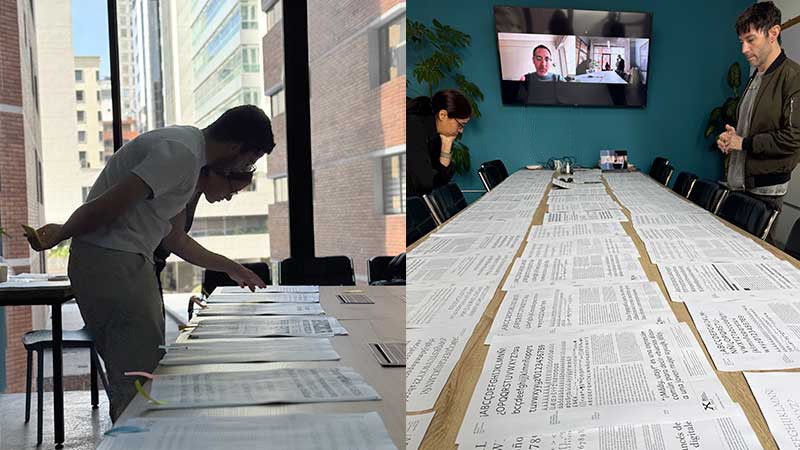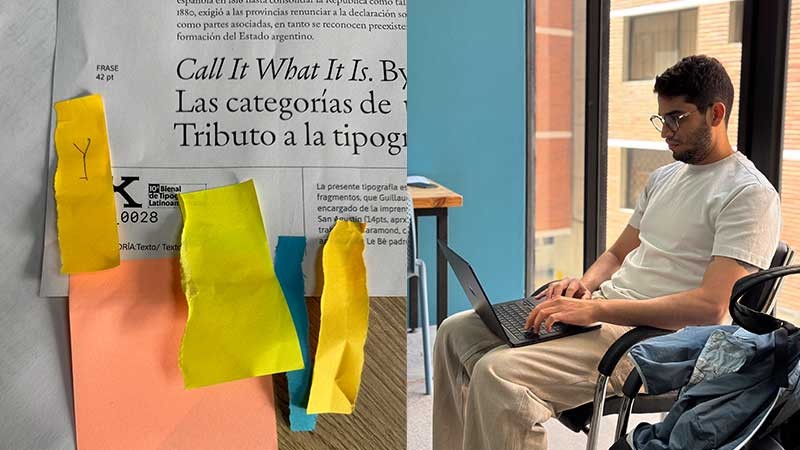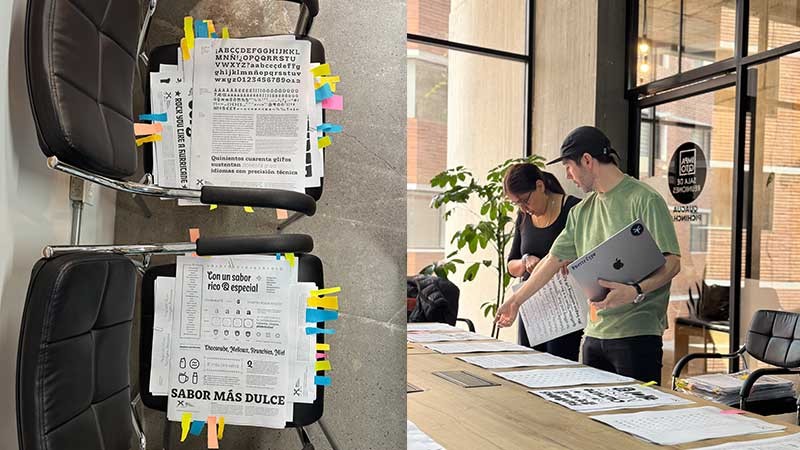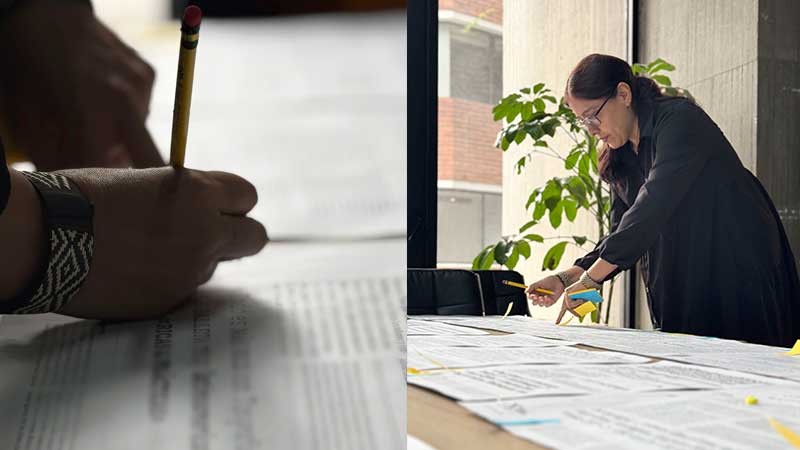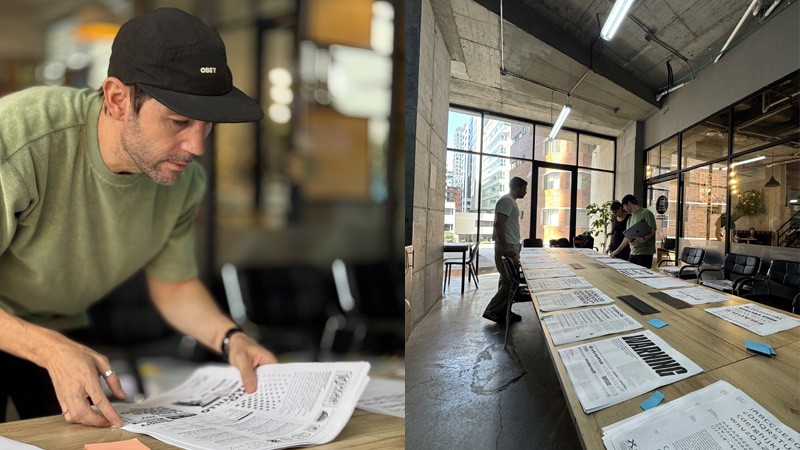
2026 Jura
Jura Tipos Latinos 2026
Por Esteban Salgado M., Coordinador General de la Jura
La Bienal de Tipografía Latinoamericana Tipos Latinos llega a su décima edición en un momento particular de su historia. Veinte años después de su inicio, no solo se consolida como un espacio de referencia para la tipografía en la región, sino que también se enfrenta a la necesidad de revisarse, actualizarse y proyectarse hacia el futuro. Esta edición marca, además, un hito importante, por primera vez la jura presencial se realizó en Quito, Ecuador, recuperando el valor del encuentro físico entre jurados como instancia clave de discusión, contraste y camaradería.
El proceso que dio forma a Tipos Latinos 10 comenzó en junio de 2025, con un enfoque claro en reorganizar el funcionamiento interno de la bienal. A partir de la creación de comisiones de trabajo, el comité pudo distribuir responsabilidades, estructurar y documentar procesos para la construcción de protocolos que permitan sostener y mejorar la bienal en el tiempo. Este modelo no solo hizo más eficiente la gestión, sino que también abrió la participación a distintos miembros, incorporando experiencias y perspectivas diversas desde cada país sede.
Uno de los cambios más relevantes fue la implementación de un sistema híbrido: una etapa de preselección virtual seguida por una jura presencial. Este modelo permitió optimizar el tiempo de los jurados y, al mismo tiempo, generar una instancia final de discusión más precisa. El resultado fue una selección sólida en un contexto de crecimiento significativo: en esta edición se recibieron 768 proyectos, una cifra que prácticamente duplica el promedio histórico de la bienal. De ese conjunto, el jurado seleccionó 75 proyectos y otorgó 3 Constancias de Excelencia.
Este crecimiento también estuvo acompañado por un trabajo sostenido en comunicación. A través de una coordinación entre sedes, se fortaleció la presencia de Tipos Latinos en redes sociales, amplificando el alcance de la convocatoria en distintos países. Paralelamente, se revisaron y actualizaron las bases de participación, reincorporando la categoría Diseño con fuentes latinoamericanas.
Otro frente importante fue el sitio web. En esta edición se realizó una actualización integral que incluyó la recuperación y organización de la información histórica de todas las bienales anteriores, la creación de un repositorio de catálogos y la mejora del sistema de inscripciones y preselección. Este trabajo no solo responde a una necesidad operativa, sino que posiciona a Tipos Latinos como un archivo activo de la tipografía latinoamericana.
La jura estuvo a cargo de Yanina Arabena (Argentina), Iván Castro (El Salvador), Yorlmar Campos (Venezuela), Fermín Guerrero (Uruguay) y Vanessa Zúñiga (Ecuador). Su participación, tanto en la etapa virtual como en la presencial, fue fundamental para sostener un proceso riguroso y abierto al diálogo. Las decisiones tomadas reflejan una escena tipográfica en expansión, con una diversidad de enfoques que va desde desarrollos técnicos complejos hasta propuestas experimentales que amplían los límites del campo.
La selección de esta edición deja ver con claridad el momento que atraviesa la tipografía en América Latina. Hay una mayor madurez en los procesos, una conciencia más clara del contexto y una relación más crítica con las herramientas disponibles que están mutando constantemente.
Este contexto también plantea una pregunta necesaria: qué rol debe asumir Tipos Latinos más allá de la bienal. Mantener una actividad continua permitiría fortalecer su impacto, ya sea a través de programas formativos, desarrollo de contenidos, expansión del archivo o generación de nuevas instancias de encuentro. En un escenario donde la disciplina sigue creciendo, la bienal puede convertirse en una plataforma activa que acompañe ese proceso.
En términos de producción, el comité tomó la decisión de establecer un único catálogo regional en formato digital, distribuido desde Tipos Latinos a todas las sedes. La versión impresa quedará a cargo de cada país, en función de sus posibilidades.
Nada de esto hubiera sido posible sin el trabajo de quienes integraron las distintas comisiones y asumieron responsabilidades específicas en cada etapa del proceso. Esta edición es, en gran medida, el resultado de un esfuerzo colectivo que permitió reactivar la bienal, organizar la jura proyectando las exhibiciones y actividades que se realizarán en distintos países de la región.
Finalmente, agradezco a todas las personas que contribuyeron a hacer posible esta edición. A la Universidad San Francisco de Quito por acoger la jura presencial, a Estudio Pánico por el desarrollo de la identidad visual de TL10, y a cada colega del comité regional que, desde su lugar, aportó a este proceso. La 10ª Bienal de Tipografía Latinoamericana Tipos Latinos no solo celebra lo que ha sido en estos veinte años, sino que abre un camino para lo que puede llegar a ser en las próximas décadas.
Jurado
Miembros del jurado ordenados alfabeticamente por país de procedencia.
Fermín Guerrero Uruguay
Nacido en Uruguay en 1983, Fermín Guerrero descubrió desde temprana edad su interés por la exploración visual, participando en varias exposiciones de pintura durante su infancia. En 2010, tras estudiar Diseño Industrial en Montevideo, se trasladó a Suiza para estudiar Comunicación Visual en la Haute École d’Art et de Design (HEAD – Genève), donde se graduó con honores de primera clase. Este éxito académico lo condujo a Inglaterra, donde completó la prestigiosa Maestría en Diseño de Tipografías de la Universidad de Reading, graduándose con “Distinction” en 2015. Durante sus estudios combinó la formación académica con el trabajo independiente, obteniendo múltiples premios y reconocimientos a lo largo de su trayectoria. En 2022 fundó Fuerte, su propio estudio de diseño tipográfico, cuyas tipografías han alcanzado reconocimiento internacional. Tras ocho años en los Emiratos Árabes Unidos como Diseñador Gráfico Senior para Trienal de Arquitectura de Sharjah, regresó a vivir a Montevideo, Uruguay. IG: @fuertetype
Palabras de apertura y conversación sobre la Jura de TL10 en Quito, Ecuador